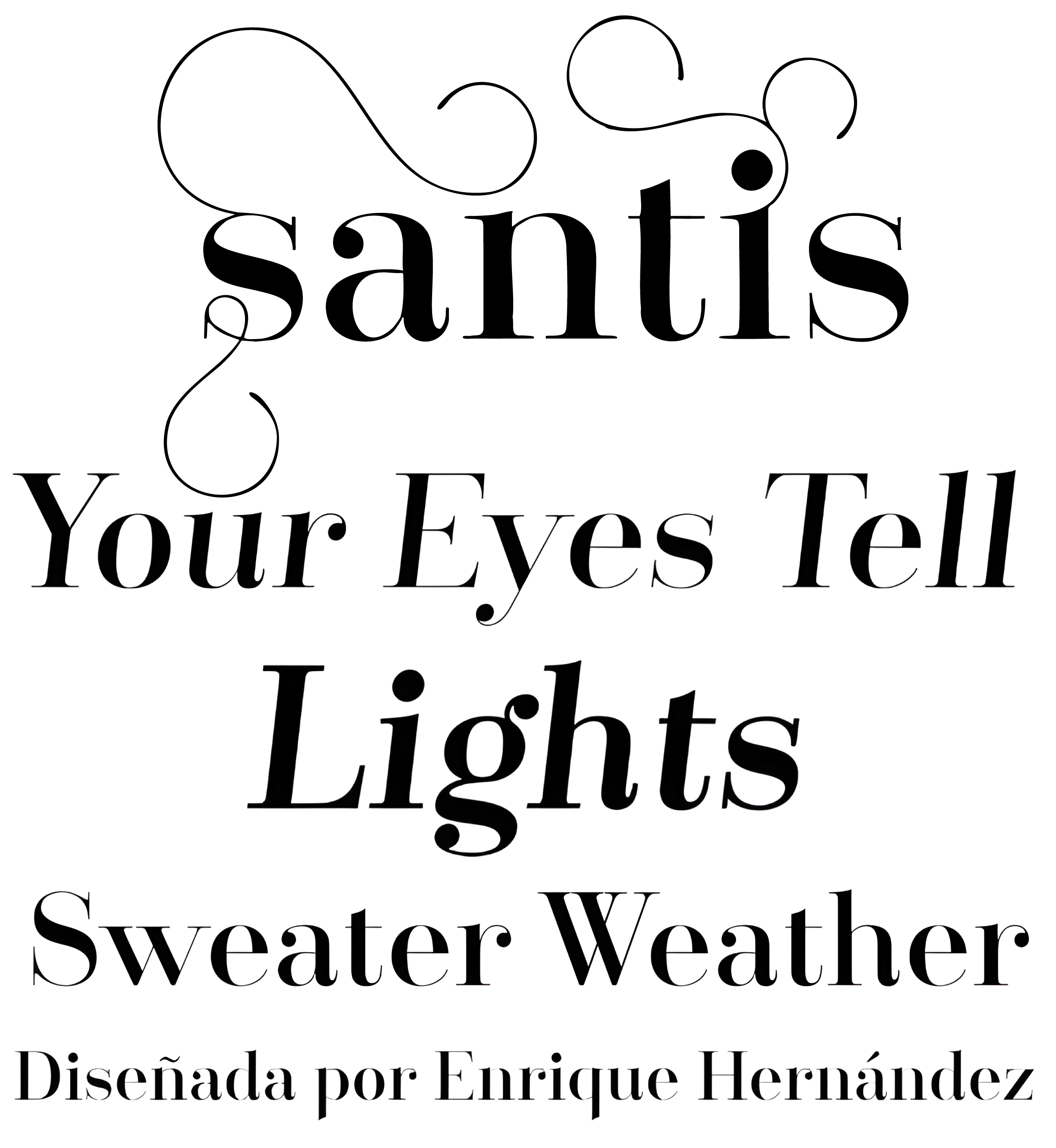
| Año | 2013 |
| Créditos | Enrique Hernández |
| Descripción | Santis es un tipo multiface, especial para logotipos, marcas, revistas y mundo editorial. Especial para marcar tendencias en moda y diseño. La particularidad de esta fuente es que se puede leer fácilmente, incluso cuando se aplican letras de tipo swash. Es una fuente basada en Didot. La versatilidad de Santis puede mostrar armoniosamente una palabra o frase. Santis tiene 1017 glifos con caracteres alternativos, números y adornos de ligaduras especialmente creados para un mejor diseño. Para obtener mejores resultados, utilícela con Open Type. Diseñado por Enrique Hernández con el apoyo técnico de Daniel Hernández. |